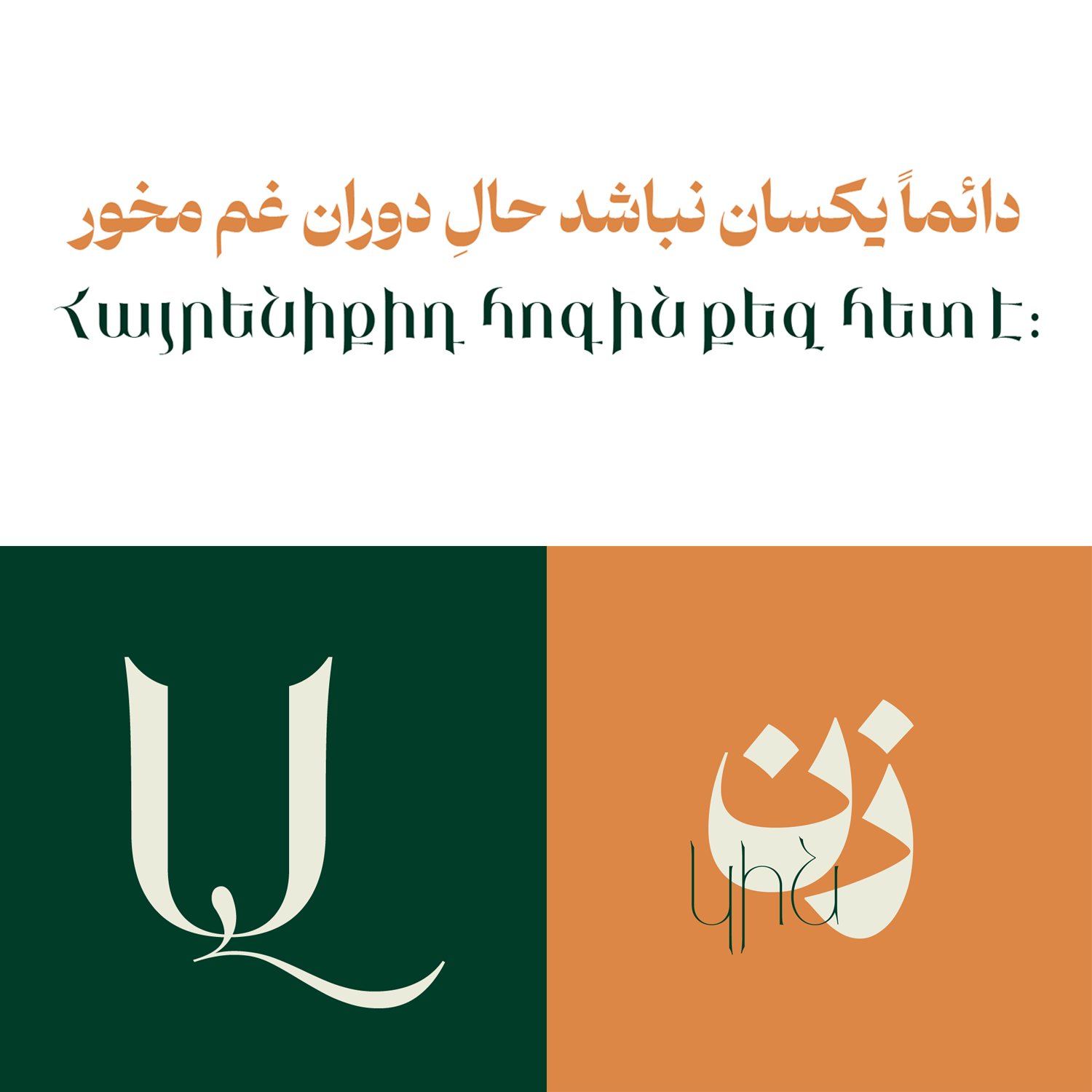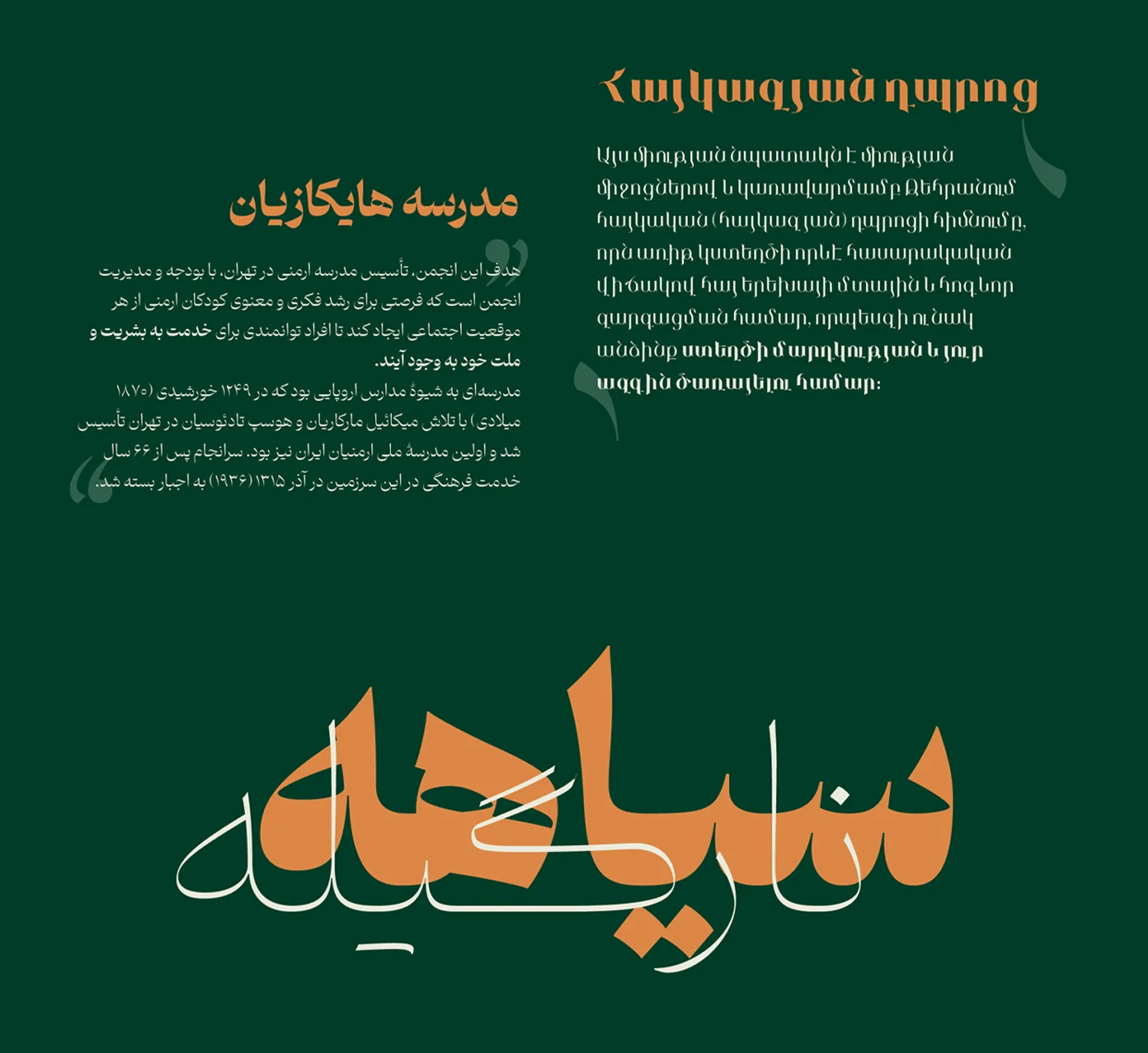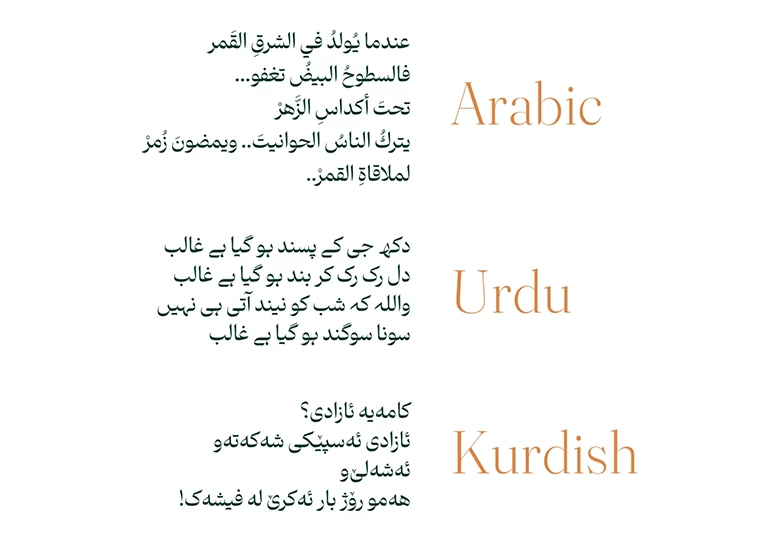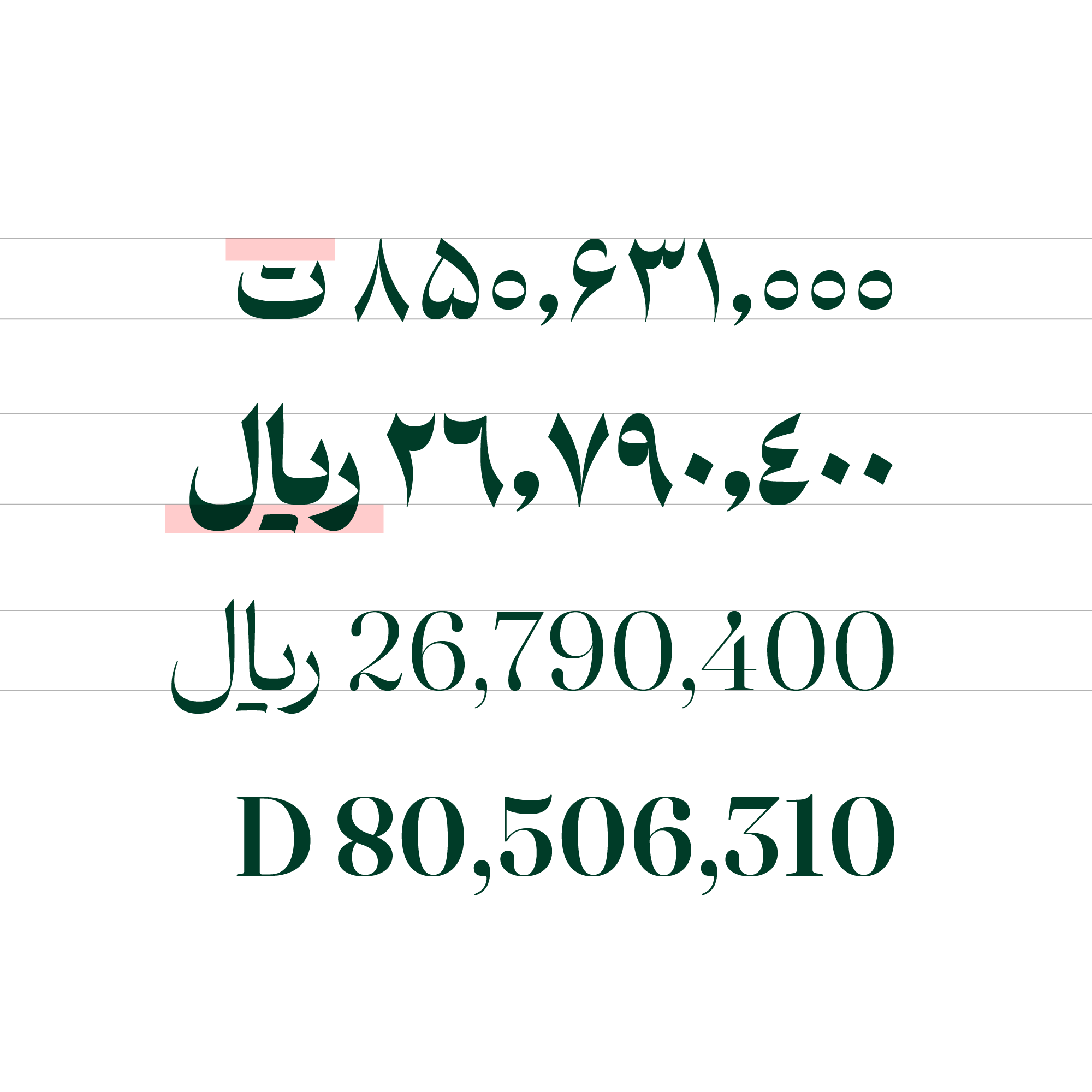
فونت دوران (Doran)
آغاز تولد فونت دوران (به انگلیسی: Doran) از یک ایده توسط فرشته ایرانشاهی شروع شد. این فونت بر اساس نیازی که برای دنیای مد و فشن مورد نیاز بود با وام گرفتن از خطوط ثلث شروع شد؛ کمکم ایده توسعه داده شده و با افزودن چاشنی از فونت نستعلیق و در نهایت خط نسخ به خروجی نهایی فونت دوران مبدل شد.
فونتی که ضمن طراحی جسورانه خود، حسابی با تلفیقی از خطوط مختلف پخته شده و چیزی است که میتواند در عین اصالت و زیبایی، برای استفاده در مواردی همچون تبلیغات در دنیای مد و فشن انقلابی ایجاد کند. این فونت پر از منحنیهای متنوع است و برای پیدا کردن یک پهنای ثابت در بخشی از آن باید ساعتها زمان صرف شود.
تلفیق این فونت با نستعلیق زیبایی خاص و مهربانی به فونت دوران داده است که در ادامه این پست از سایت فونتچی به بررسی مشخصهها، ویژگیها و امکاناتی که فونت Doran دارد خواهیم پرداخت. اما پیش از شروع بد نیست بدانید که توسعه این فونت توسط رضا بختیاری فرد صورت گرفته است.
معرفی و بررسی فونت دوران (Doran)
فونت دوران را میتواند در دسته فونتهای عنوان قرار داد. این فونت دارای منحنیهای مختلف در تمامی حروف است که در بخش مفصلها بسیار نرم و بدون شکستگی است. اما در مقابل لبههایی تیز داشته و در بخش تقاطع هر حرف، منحنیها به مویی بند هستند.
قلمی با طراحی مشابه که برای استفاده در دنیای مد و فشن مناسب است به نام فونت پیکان نیز وجود دارد که این فونت نیز بر اساس خط نسخ طراحی شده و مشابه فونت دوران دارای منحنیهایی ضخیم و شکستگیهای نازک است؛ با این تفاوت که اغراق بیشتری روی آن صورت گرفته، ضخیمتر و دارای شکستگیهای تیزتر است.
همین مشخصهها دست بهدست هم داده تا در نهایت فونتی بسیار لطیف و در عین حال با کنتراست بالا باشد که در استفاده در بخشهایی همچون عناوین و تیترها عامل و تلنگری برای توجه بیشتر است. میتوان این فونت را در کنار فونتهایی که کلاسیک و کنتراست بسیار بالاتری دارند به صورت ترکیبی استفاده کرده و یک خروجی عالی از آن گرفت.
سبک طراحی و وزن فونت متغیر دوران
فونت دوران دارای ۸ وزن مختلف است که شامل Thin, Light, Regular, Medium, Bold, ExtraBold, Black و ExtraBlack هستند. هر یک از این وزنها به صورت کاملا استاندارد در تمامی حروف و منحنیها طراحی شده است که میتوانید متنهایی خارقالعاده را با آن خلق کنید.
پشتیبانی از زبان های مختلف
فونت دوران علاوه بر زبان فارسی که شامل اعداد فارسی است؛ از زبانهای عربی، کردی، اردو، ارمنی و انگلیسی نیز پشتیبانی میکند. در زبانهای عربی، فارسی و انگلیسی، اعداد متناسب با هر زبان هستند که با توجه به در دسترس بودن این فونت در قالب چند نسخه، میتوانید ترکیبی از زبانها را بر اساس اعداد مختص همان زبان در اختیار داشته باشید.
با توجه به رسمخط یکسانی که سایر زبانهای خاورمیانهای مثل عربی، کوردی و اردو در مقایسه با فارسی دارند، از این قلم میتوانید بهسادگی در این زبانها استفاده کنید. حروفی که مشترک هستند دارای گلیف اشتراکی بوده و زبانهایی که شکل ظاهری حروف متفاوت است، گلیف اختصاصی خود را در اختیار دارند که در صورت تایپ با همان زبان صفحه کلید قابل استفاده خواهد بود.
فونت فارسی دوران را میتوان نمادی از نسخه امروزی خط نستعلیق درنظر گرفت که با خط ثلث تلفیق شده است. در این فونت اعداد گاه در نسخهای صرفا شامل اعداد همان زبان هستند که خبری از زبان لاتین در آن نیست؛ گاه فقط شامل اعداد لاتین انگلیسی هستند؛ یا اینکه ترکیبی از هر دو اعداد را شامل میشوند. بسته به اینکه از کدامیک استفاده کنید، در صورت تایپ انگلیسی، اعداد فارسی نمایش داده خواهد شد.
چنین ویژگی برای استفاده در وب سایتها که رابط کاربری از یکسو و سئو سایت با توجه به نمایش اعداد به صورت فارسی یا انگلیسی تاثیر سئویی بر روی سایت دارد از اهمیت بالایی برخوردار است.
پشتیبانی از ترکیبها و حروف جایگزین
دومین ویژگی مهم فونت Doran قابلیت استفاده از حروف ترکیبی است. یعنی شما بتوانید برخی از حروف خاص را به شکلهای مختلفی تایپ کنید.
در این فونت امکان تایپ حروف «ب، ی، س، ث، ک، ه، م» دارای ساختارهای مختلفی هستند که در بخش انتهایی هر کلمه میتوانید با استفاده از راهنمایی که در بسته فونت وجود دارد، حروف را در قالبهای متنوعی که بر پایه خطوط نستعلیق، ثلث و نسخ درنظر گرفته شده است تایپ کنید.
پشتیبانی از اعداد و کاراکترهای خاص هر زبان
برای زبانهای کردی، اردو و عربی نیز علاوهبر اعداد، اعراب گذاری و استفاده از کاراکترهای خاص تزئینی در این فونت گنجانیده شده است که نمونهای از آن را در تصویر زیر مشاهده میکنید.
دارای گلیف اختصاصی تومان و ریال
از نسخه دوم فونت Doran دو گلیف اختصاصی برای نمایش واحد پولی «تومان» و «ریال» به این فونت افزوده شده است که میتوانید بهمنظور بهبود تجربه کاربری در سایت یا اپلیکیشن خود استفاده کنید. برای این منظور کافی است در نسخه وریبل از تنظیمات Stylistic Sets 7 که در فایل راهنما درون فونت توضیح داده شده در کدهای CSS خود استفاده کنید.